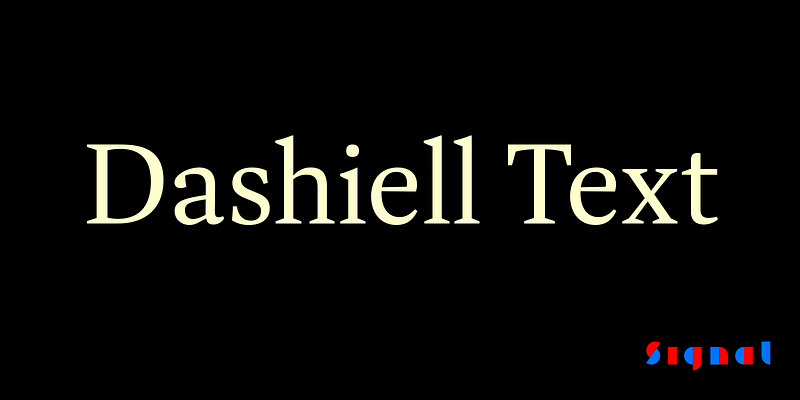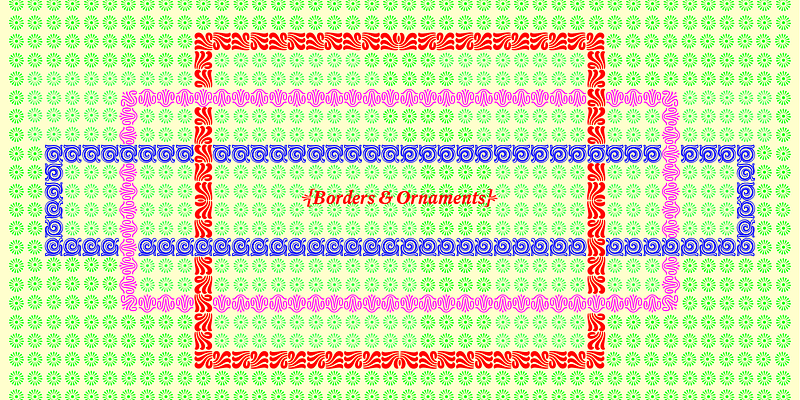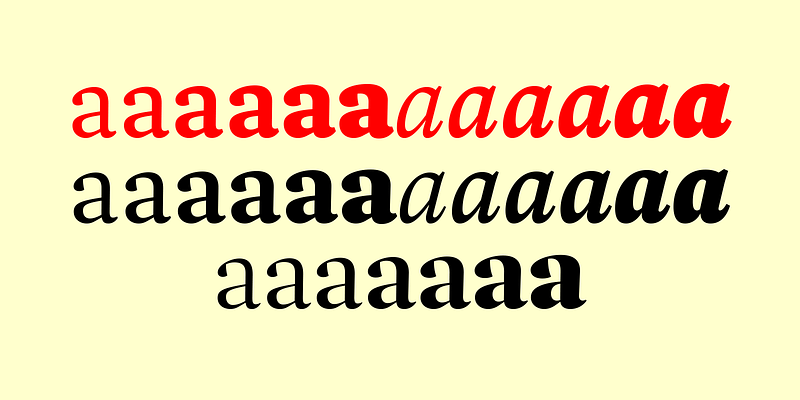
Dashiell은 가독용으로 제작되었습니다. 시력이 나쁜 독자에 의해 디자인된 이 서체는 Caslon의 따스함과 솔직함에 Garamond의 우아함을 가미했습니다. 서체에는 비례 및 표 라이닝과 전 스타일의 도형, 작은 대문자, 대소문자를 구분하는 구두점과 구분 기호, 선별된 테두리와 장식 기호 등이 포함됩니다.